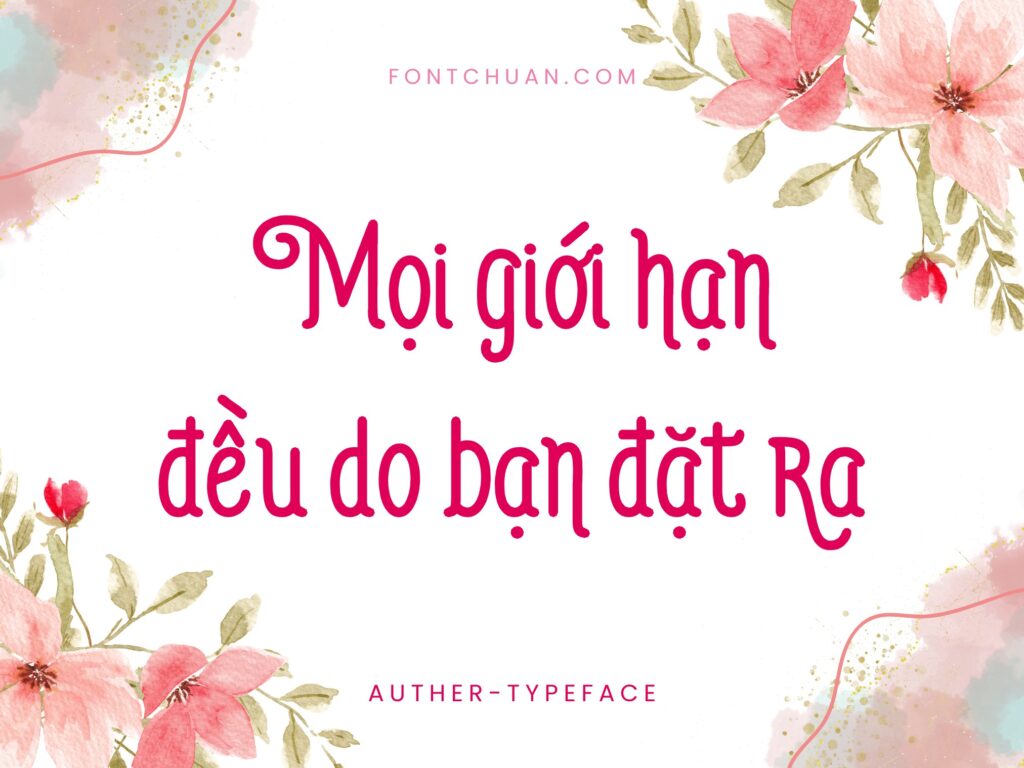
Font iCiel Auther Typeface Việt Hóa
Auther Typeface là một font chữ kết hợp giữa phong cách hiện đại và cổ điển, được thiết kế bởi Seniors Studio. Với thiết kế monoline tinh tế, font này mang đến sự thanh lịch và độc đáo cho các dự án thiết kế. Để hỗ trợ cộng đồng thiết kế Việt Nam, Iciel đã Việt hóa font Auther Typeface, giúp font này hỗ trợ đầy đủ tiếng Việt cùng hơn 200 ngôn ngữ khác. Phiên bản Auther Typeface Việt hóa đã được thành viên Font Chuẩn sưu tầm và đăng tải, mang đến sự lựa chọn đa dạng cho các nhà thiết kế.
Về đặc điểm thiết kế, Auther Typeface sở hữu các ký tự monoline với đường nét đồng nhất, kết hợp giữa yếu tố cổ điển và hiện đại. Font này rất phù hợp cho các thiết kế như logo, thiệp mời, poster, nhãn mác, thiệp chúc mừng, tiêu đề thư và bìa sách. Ngoài ra, Auther Typeface cũng là lựa chọn lý tưởng cho các ngành nghề như quảng cáo, thiệp cưới, ẩm thực và giáo dục, mang lại phong cách chuyên nghiệp và thu hút. Font này cũng thích hợp để sử dụng trong các sự kiện như lễ hội, sinh nhật và Valentine.